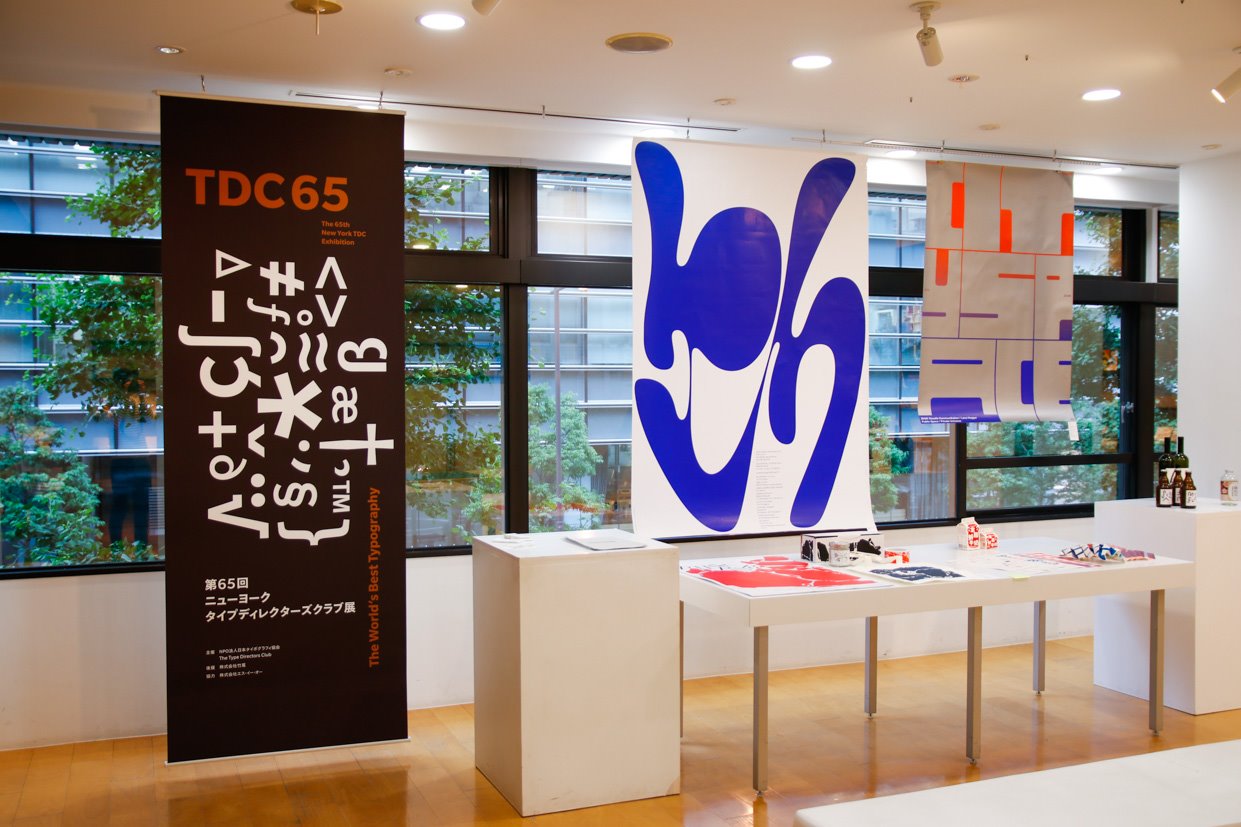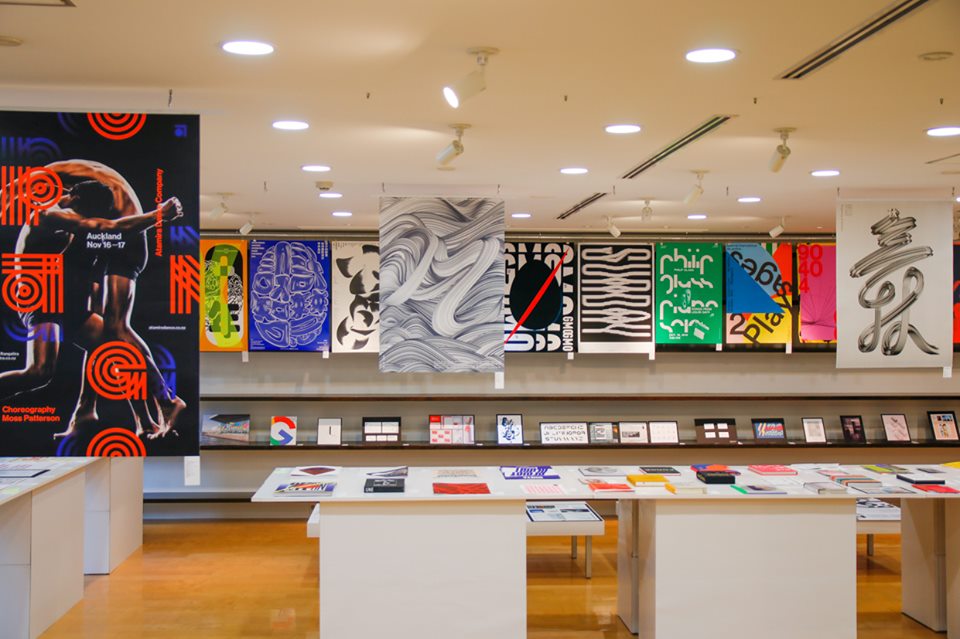
第65回ニューヨークタイプディレクターズクラブ展
TDC65 Exhibition
ニューヨークに拠点を持つThe Type Directors Clubにより選出された、この冬発刊のANNUALに掲載される、優秀なタイポグラフィ作品をいち早くご覧いただけます。
TDC65はカラフルな作品が多く、ギャラリーは華やかな雰囲気です。